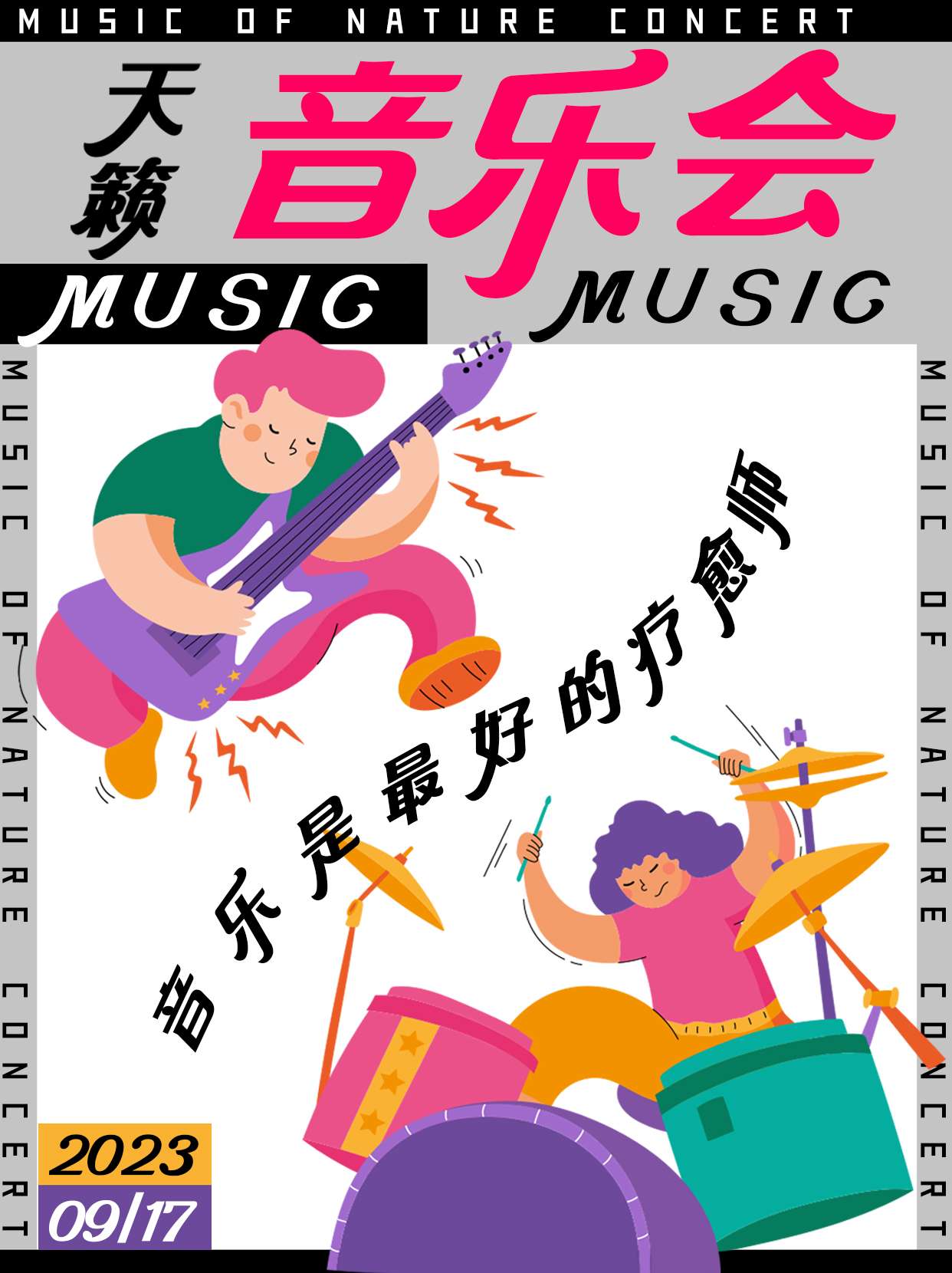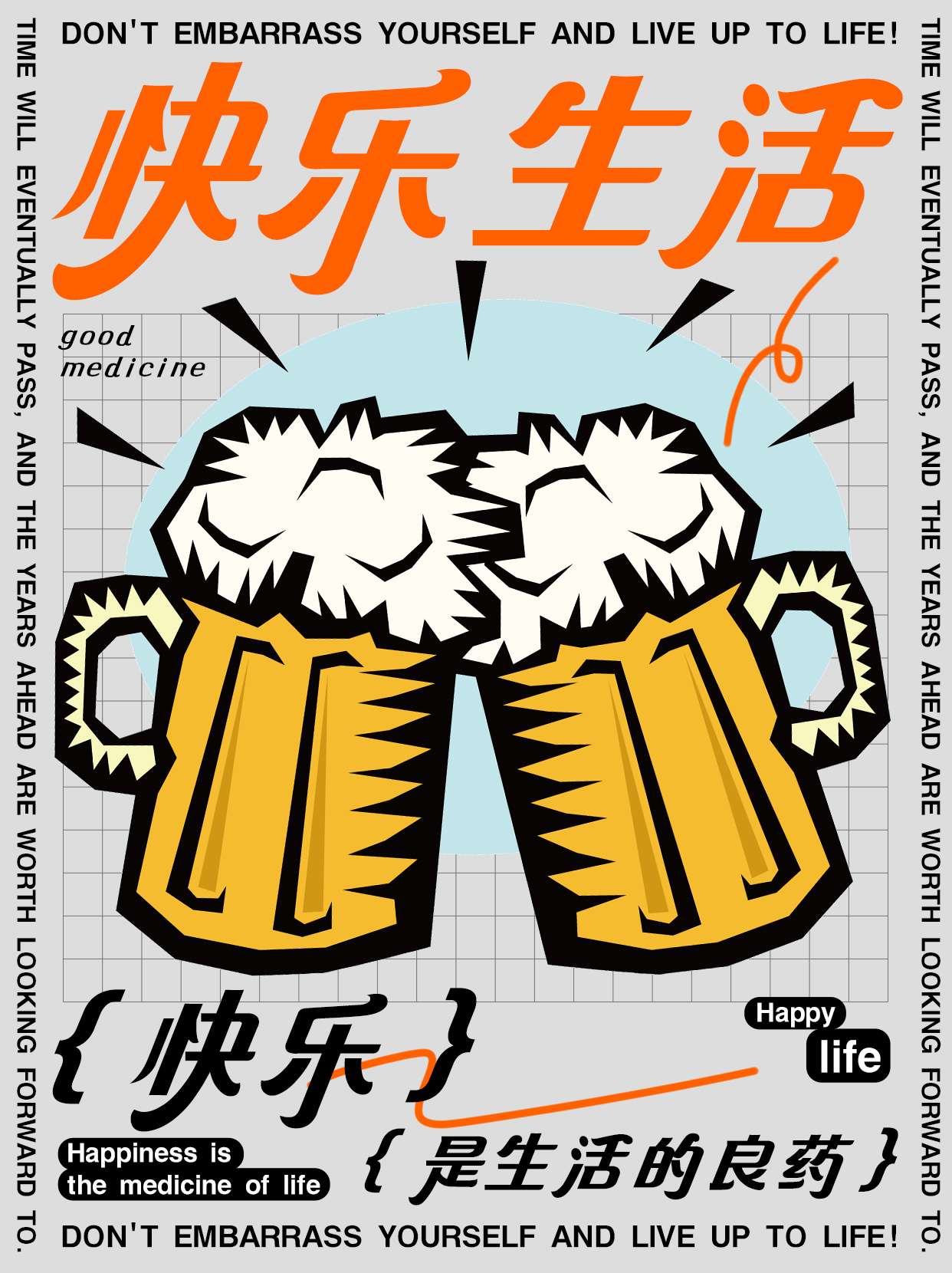
造字侠郝刚快乐简 微黑
PlayFont-HappyGB
快乐是生活的良药
采用中西结合的设计手法,一方面糅合西文斜体装饰风格的浪漫优雅,字体倾斜112度;一方面运用汉字隶书笔画的撇、捺错落变化,在蚕头燕尾的韵味中,构建斜体字的韵律感、节奏感;在微妙的平衡感中,创造轻松明快的自洽节奏,也是对字体美感的均衡把控。